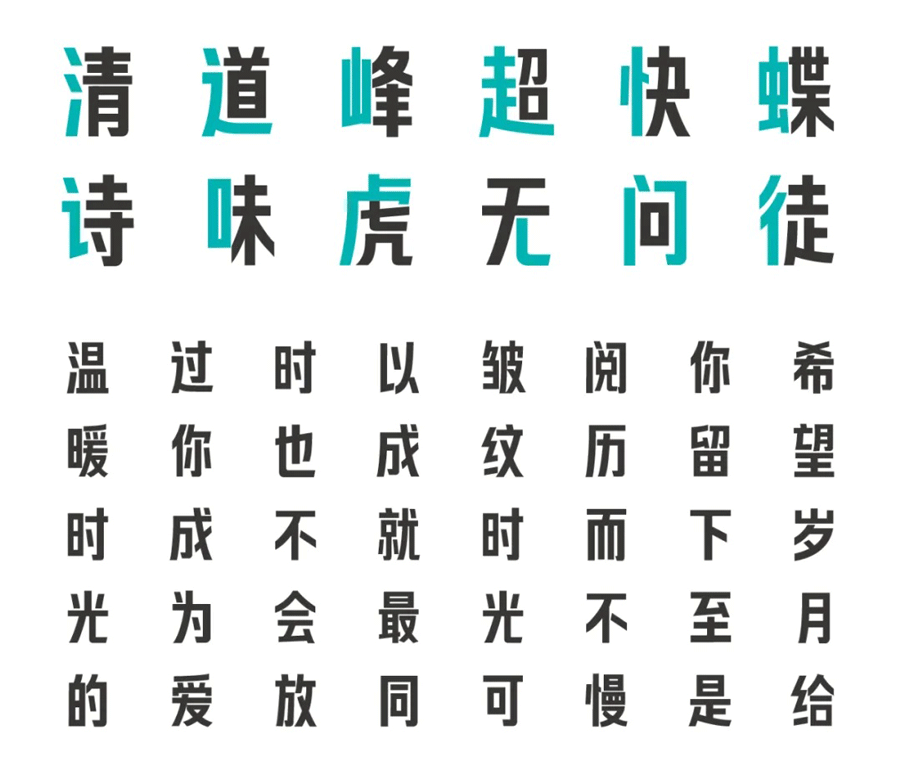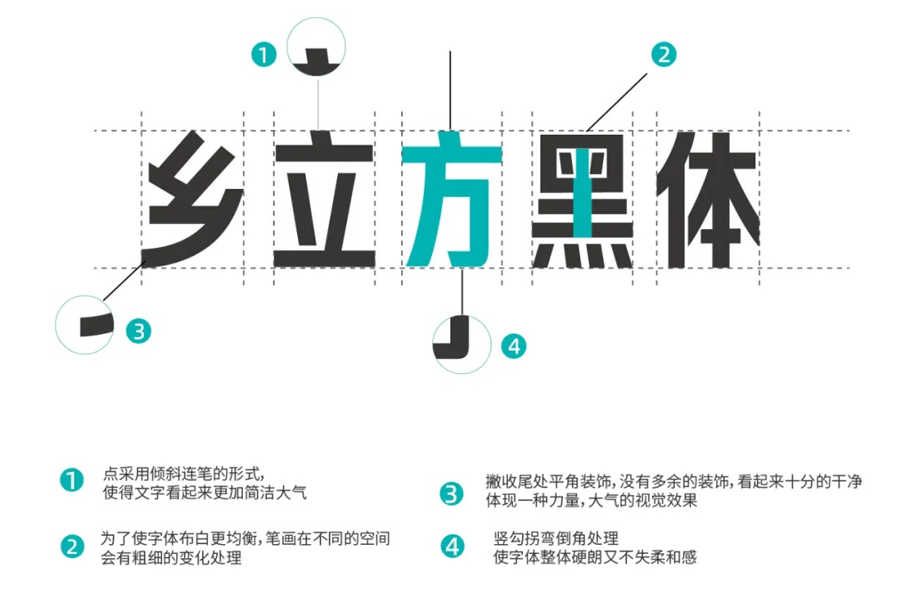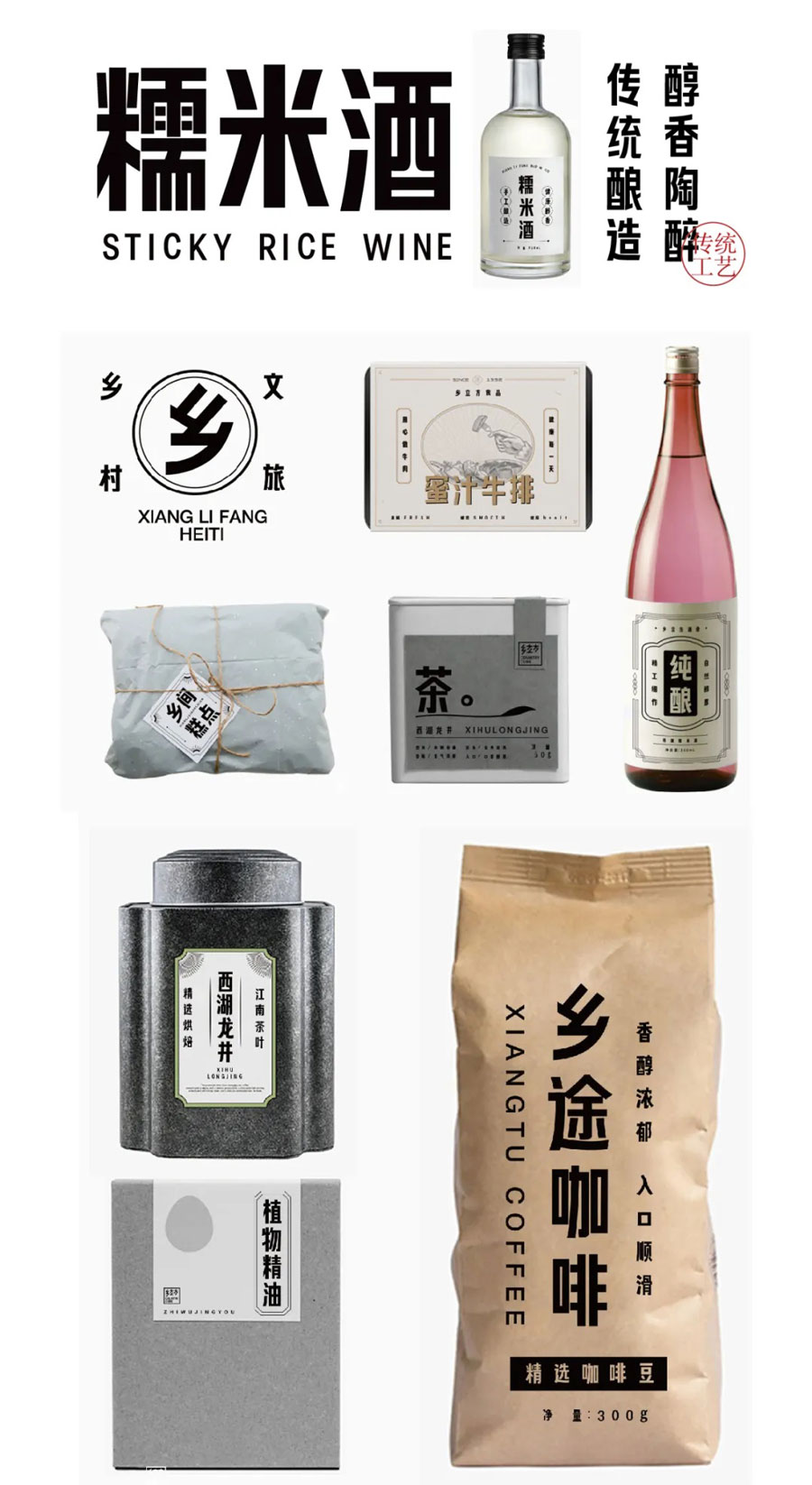
乡立方黑体
乡立方黑体是由浙江乡立方乡村发展集团旗下火石品牌字体部主导设计的免费可商用中文字体,专为乡村主题设计而兼具现代感,个人与企业均可直接用于商业场景(如海报、包装、广告等)。
乡立方黑体是由浙江乡立方乡村发展集团旗下火石品牌字体部主导设计的免费可商用中文字体,灵感源于乡村中充满时代感的刷墙字体,同时融合了乡立方 “乡村振兴” 的品牌理念。
乡立方黑体
这款字体采用 80:100(宽度:高度)的字面比率,整体修长挺拔,中宫紧凑。笔画设计强调视觉统一性,避免过度紧凑带来的压迫感,同时兼具和谐自然与时尚感。
乡立方黑体
乡立方黑体总共囊括了 4500 个基础常用字,可覆盖日常 98% 的使用范围,未来还将根据实际情况逐步补充和完善字库。此外,乡立方黑体实行免费授权使用策略,允许个人和企业免费使用,包括商业用途,如广告设计、自媒体、电商平台等。
乡立方黑体